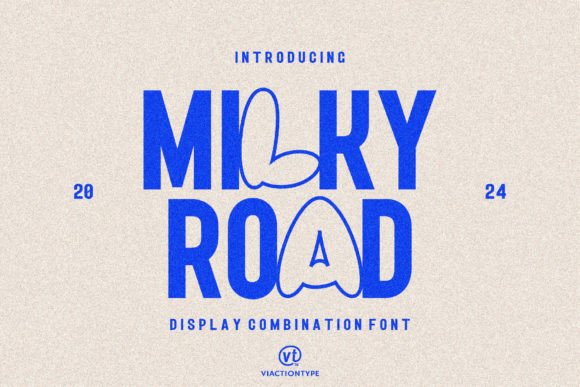
Milky Road
適切なデザイン要素を見つけるのは難しい場合がありますが、Milky Roadは作品を即座に引き立てる優れたコレクションを提供します。
POD(オンデマンド印刷)製品、結婚式の招待状、またはソーシャルメディアのグラフィックを作成している場合でも、Milky Roadは理想的です。